- Buka aplikasi YouTube atau kunjungi situs YouTube di peramban atau browser. Pilih video yang ingin kamu tonton. Pastikan video tersebut memiliki subtitle (CC) atau closed captions yang aktif.
- Klik ikon CC yang berada di bagian kanan bawah video.
- Klik ikon roda gigi (pengaturan) yang juga ada di bagian kanan bawah video.
- Pada menu yang muncul, pilih opsi Subtitles/CC dan kemudian klik Options/Opsi di sebelahnya.
- YouTube memberikan beberapa pilihan kustomisasi untuk subtitle. Kalau kamu ingin mengubah jenis font saja maka klik "Jenis Font".
- Setelah selesai mengatur tampilan subtitle sesuai keinginan, pengaturan ini akan otomatis tersimpan dan siap digunakan untuk semua video yang akan kamu tonton menggunakan akun YouTube kamu. Gampang banget, kan, caranya?
Apakah Bisa Mengubah Font Subtitle di YouTube? Begini Caranya!
Saat menonton video favorit di YouTube, kamu pasti sudah familiar dengan fitur subtitle yang ada di sana. Subtitle di YouTube bukan hanya sekadar pelengkap, tetapi memiliki peran penting, terutama bagi mereka yang kesulitan dengan bahasa asing atau memiliki gangguan pendengaran. Pengguna juga bisa memilih apakah menonton video menggunakan subtitle atau tidak.
Kalau kamu mulai bosan dengan tampilan font yang monoton saat menonton video di YouTube, tak perlu khawatir. Kini, YouTube memungkinkan penggunanya untuk menyesuaikan tampilan subtitle, termasuk jenis font, ukuran, dan warna, agar lebih nyaman saat dilihat. Ingin tahu caranya? Yuk, baca artikel ini sampai habis!
1. Cara mengubah font subtitle di YouTube
Cara mengubah font subtitle di YouTube (dok.pribadi/Reyvan Maulid) YouTube menyediakan berbagai pilihan font subtitle untuk disesuaikan dengan berbagai kebutuhan pengguna. Memahami karakteristik dari setiap jenis font mulai dari yang formal seperti serif hingga yang kasual dan artistik seperti kursif bikin pengguna dapat memilih font yang paling sesuai untuk kenyamanan dan estetika saat menonton video. Begini caranya mengubah font subtitle di YouTube. Simak dan perhatikan langkah-langkahnya berikut:
Selain pengaturan font subtitle, YouTube juga menyediakan pengaturan lebih lanjut seperti ukuran font, warna teks, warna latar belakang, warna jendela, opasitas latar belakang, dan lain-lain. Oh, iya, disclaimer dulu. Cara di atas berlaku apabila kreator konten mengaktifkan fitur subtitle pada videonya. Jika tidak, maka pengubahan font tidak bisa dilakukan.
2. Jenis font subtitle yang tersedia di YouTube
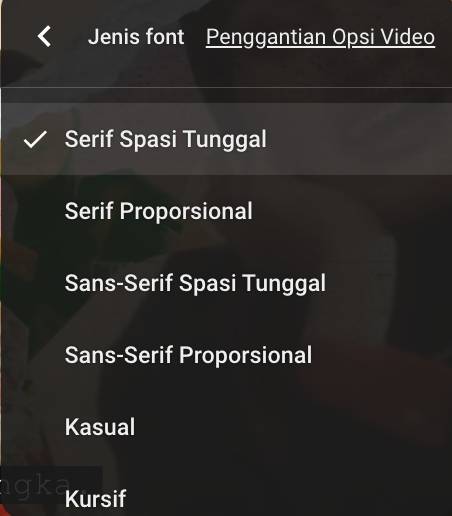
Jenis font subtitle yang tersedia di YouTube (dok.pribadi/Reyvan Maulid) Saat kamu memutuskan untuk mengganti jenis font pada subtitle, YouTube menyediakan beragam pilihan font yang bisa kamu manfaatkan untuk meningkatkan kenyamanan menonton. Selain itu, kemampuan untuk mengubah ukuran dan warna font memberi kamu kontrol penuh atas bagaimana subtitle dapat tampil di layar. Jika kamu menonton dari jarak jauh atau di layar yang lebih kecil untuk memperbesar ukuran font bisa membantu subtitle tetap terlihat dengan jelas. Begitu juga dengan pemilihan warna, di mana kamu bisa memilih kombinasi warna teks dan latar belakang yang kontras agar subtitle tetap terbaca meski video memiliki latar belakang yang kompleks. Nah, apa saja jenis font yang tersedia di YouTube? Berikut adalah rinciannya
- Serif Spasi Tunggal
- Serif Proporsional
- Sans-Serif Spasi Tunggal
- Sans-Serif Proporsional
- Kasual
- Kursif
- Kapital Kecil
Daftar font subtitle berikut bisa kamu sesuaikan dengan kebutuhan, kesukaan, dan preferensi kamu. Saat melakukan pengubahan font, kamu juga akan melihat beragam bentuk font jika kamu mengklik satu persatu jenis font yang telah dijabarkan di atas.
3. Manfaat sederhana mengubah font subtitle di YouTube
ilustrasi video YouTube (unsplash.com/Leon Bublitz) Mengubah font subtitle dapat mendatangkan manfaat dan keuntungan bagi pengguna yang sehari-hari menonton video melalui YouTube. Baik itu sebagai hiburan, pelepas penat, maupun teman di kala beraktivitas seperti nugas, karaoke bareng maupun menonton tutorial memasak, mengubah font subtitle dapat akan memberikan pengalaman menonton yang lebih personal dan nyaman. Salah satu manfaat utamanya adalah meningkatkan keterbacaan, terutama bagi pengguna yang memiliki masalah penglihatan atau merasa tidak nyaman dengan ukuran atau jenis font default yang disediakan oleh YouTube.
Pengaturan subtitle yang sesuai juga sangat membantu ketika menonton video di tempat yang pencahayaannya kurang ideal, seperti di luar ruangan atau saat malam hari. Misalnya, memilih font yang lebih tebal dan kontras dengan latar belakang video bisa membuat teks lebih mudah dibaca tanpa mengganggu kenyamanan visual. Selain itu, pengguna yang gemar karaoke di YouTube juga dapat memanfaatkan perubahan font dan warna subtitle agar lebih sesuai dengan gaya tampilan lirik yang diinginkan untuk menciptakan suasana karaoke yang lebih seru dan interaktif.
Bagi mereka yang menggunakan YouTube untuk belajar, seperti menonton tutorial atau video edukasi, mengubah font subtitle dapat membantu meningkatkan fokus. Teks yang lebih jelas akan memudahkan penyerapan informasi, terutama saat subtitle digunakan untuk memahami materi dalam bahasa asing atau konten teknis yang kompleks. Pengaturan yang tepat dapat membuat proses belajar lebih efisien dan menyenangkan. Secara keseluruhan, mengubah font subtitle di YouTube bukan hanya tentang preferensi estetika, tetapi juga tentang kenyamanan, aksesibilitas, dan optimasi pengalaman menonton bagi berbagai kebutuhan.
Berbekal cara mengubah font subtitle di YouTube yang telah dijelaskan di atas, pengguna jadi punya keleluasaan untuk menyesuaikan tampilan subtitle sesuai dengan pilihan dan preferensi kamu. Hal ini tidak hanya meningkatkan kenyamanan dalam menonton video, tetapi juga membuat pengalaman lebih menyenangkan dan inklusif. Dengan pilihan font, ukuran, warna, dan transparansi yang dapat diubah, pengguna dapat memastikan subtitle tetap jelas dan mudah dibaca, baik di perangkat kecil seperti HP maupun di layar besar seperti TV atau monitor. Yuk, langsung praktekkan!